영어 필기체 폰트를 무료로 변환해 활용할 수 있는 온라인 사이트를 소개합니다. 설치 없이 웹 브라우저에서 바로 사용할 수 있으며, SNS·메신저·블로그 등 다양한 플랫폼에서 특별한 텍스트 스타일을 적용할 수 있습니다. LingoJam을 비롯한 여러 변환 사이트와 사용 방법을 단계별로 정리했습니다.
1. 영어 필기체 변환의 필요성
SNS 프로필, 메시지, 블로그 글을 작성할 때 남들과 차별화된 글씨체는 특별한 감성을 더해줍니다. 특히 영어 필기체는 우아하고 세련된 분위기를 연출할 수 있어 많은 사용자들이 찾는 인기 텍스트 스타일입니다.
2. LingoJam 필기체 변환 사이트
LingoJam은 별도의 설치나 회원가입 없이 웹 접속만으로 다양한 영어 텍스트를 변환할 수 있는 사이트입니다.
| 항목 | 설명 |
|---|---|
| 사이트명 | LingoJam |
| 주요 기능 | 영어 필기체, 특수문자 조합, 뒤집힌 텍스트 등 제공 |
| 사용 방법 | 왼쪽 입력창에 문장 입력 → 오른쪽에서 자동 변환된 텍스트 확인 후 복사 |
3. 변환된 텍스트 활용법
❶ LingoJam
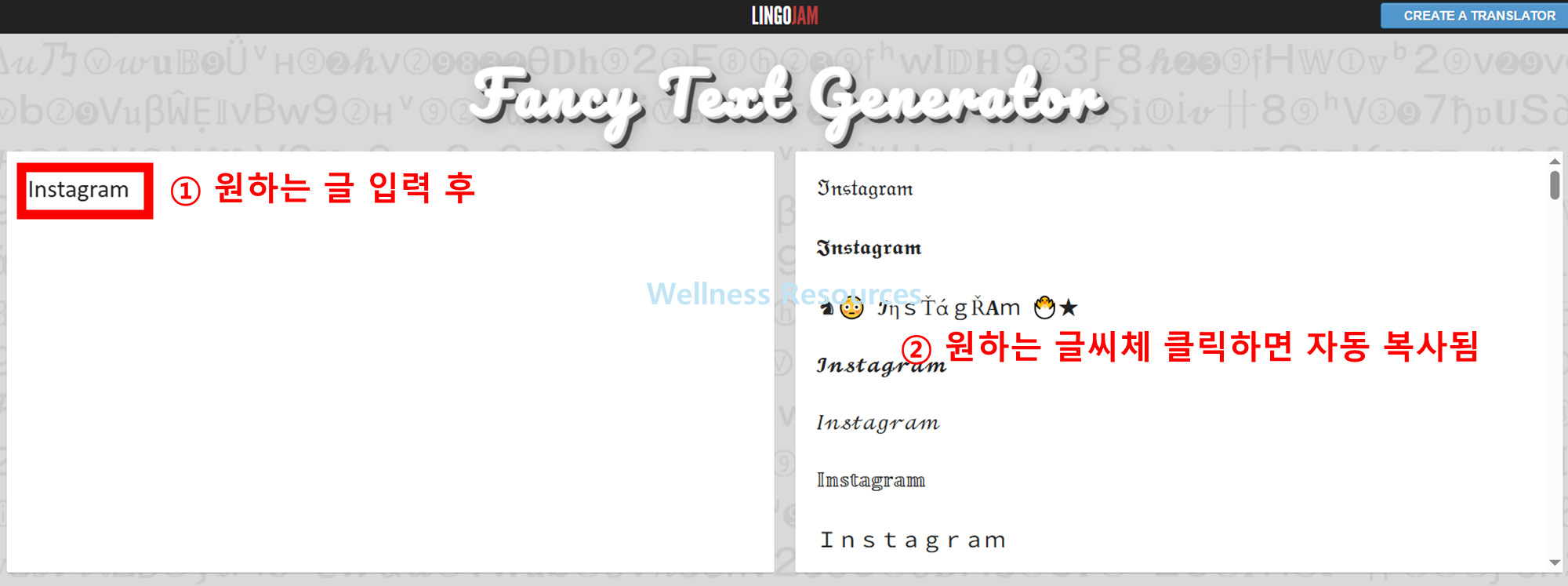
❷ Cool Symbol
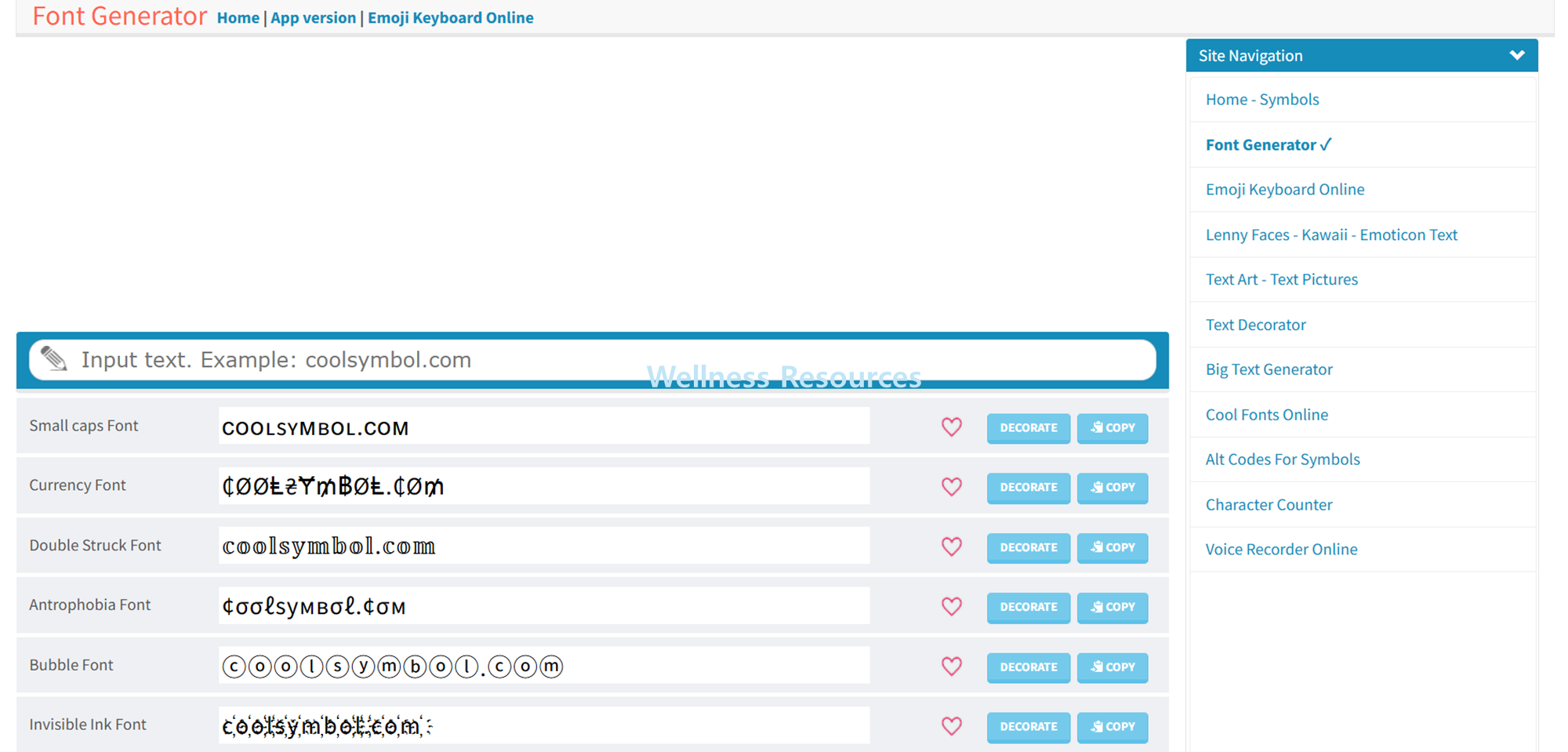
❸ Font Meme
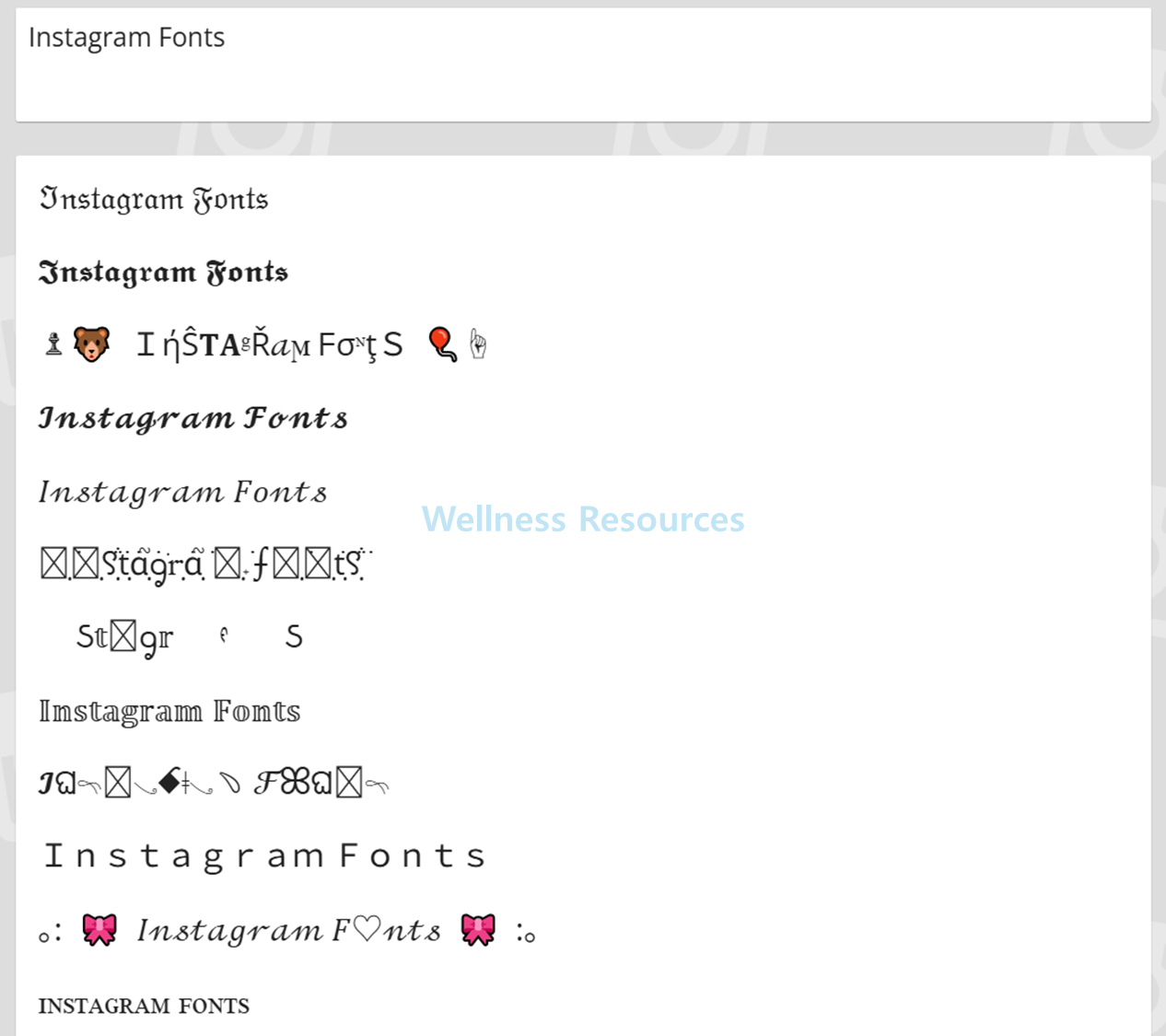
❹ IGFonts.io
❺ Piliapp
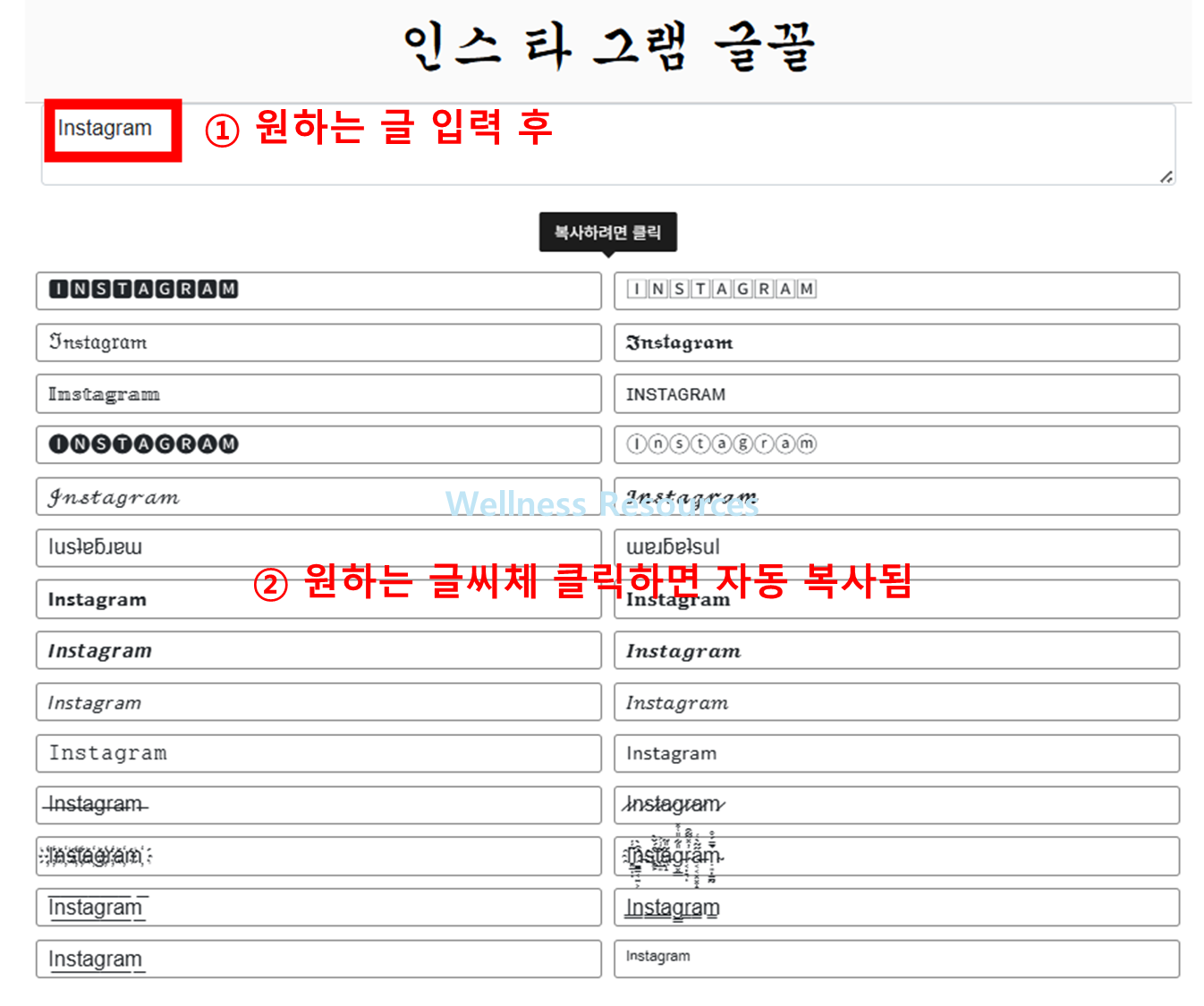
복사한 텍스트는 카카오톡, 인스타그램, 페이스북, 블로그 등 대부분의 플랫폼에서 그대로 붙여넣기 가능하며, 이미지 저장 과정이 필요 없어 빠르고 간단합니다.
4. LingoJam 외 추천 사이트
| 사이트명 | 특징 |
|---|---|
| Cool Symbol | 필기체+아이콘 조합 가능, 특수문자 디자인 제공 |
| Font Meme | 로고·폰트 스타일 변환 지원, 시각적 효과 강함 |
| IGFonts.io | 인스타그램 전용 폰트 변환, 직관적 UI |
| Piliapp | 수십 가지 텍스트 스타일 실시간 변환 |
5. 사이트별 장단점 비교
| 사이트명 | 장점 | 단점 |
|---|---|---|
| LingoJam | 설치 불필요, 다양한 텍스트 변환 | 광고 노출 많음 |
| Cool Symbol | 특수문자·아이콘 지원 | UI가 다소 복잡 |
| Font Meme | 폰트·로고 제작 가능 | 이미지 기반 변환 위주 |
| IGFonts.io | 인스타그램 맞춤형 | 기능이 제한적 |
| Piliapp | 다양한 스타일 | 일부 글씨체는 가독성 떨어짐 |
6. 사용 시 주의사항
- 너무 과도한 특수문자 사용은 가독성을 해칠 수 있음
- 문서 작업용보다는 SNS나 메시지 장식용으로 활용하는 것이 적합
📌 FAQ
Q2. 변환된 텍스트는 어디에서나 사용할 수 있나요?
A2. 네, 카카오톡·인스타그램·블로그·페이스북 등 텍스트 입력이 가능한 대부분의 환경에서 사용 가능합니다. 다만 일부 오래된 앱에서는 호환이 제한될 수 있습니다.